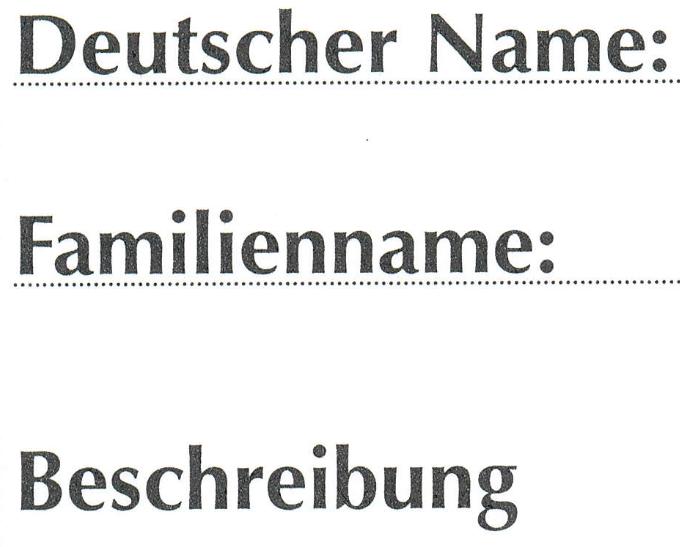
Suche Schriftart
ich habe bereits auf Seiten wie z.B. www.myfont.de gesucht, aber es gibt da ja so wenige Schriftarten :rolleyes:.
Also folgendes Problem, ich führe mein Berichtsheft (für meine Ausbildung) am PC. Ziel ist es die Vorlagen so original wie möglich nachzubilden.
Dazu suche ich noch die richtige Schriftart (siehe Anhang).
Kennt jemand diese Schriftart, bzw. wisst ihr, wie man diesen Stil/diese Art von Schriftart nennt?
Schöne Schrift, die früher oft verwendet wurde. Ich tippe auf Optima Bold oder Zapf Humanist 601 Bold. Üblicherweise wurde Optima verwendet.
die Optima scheint die richtige zu sein (obwohl die ja fast gleich sind).